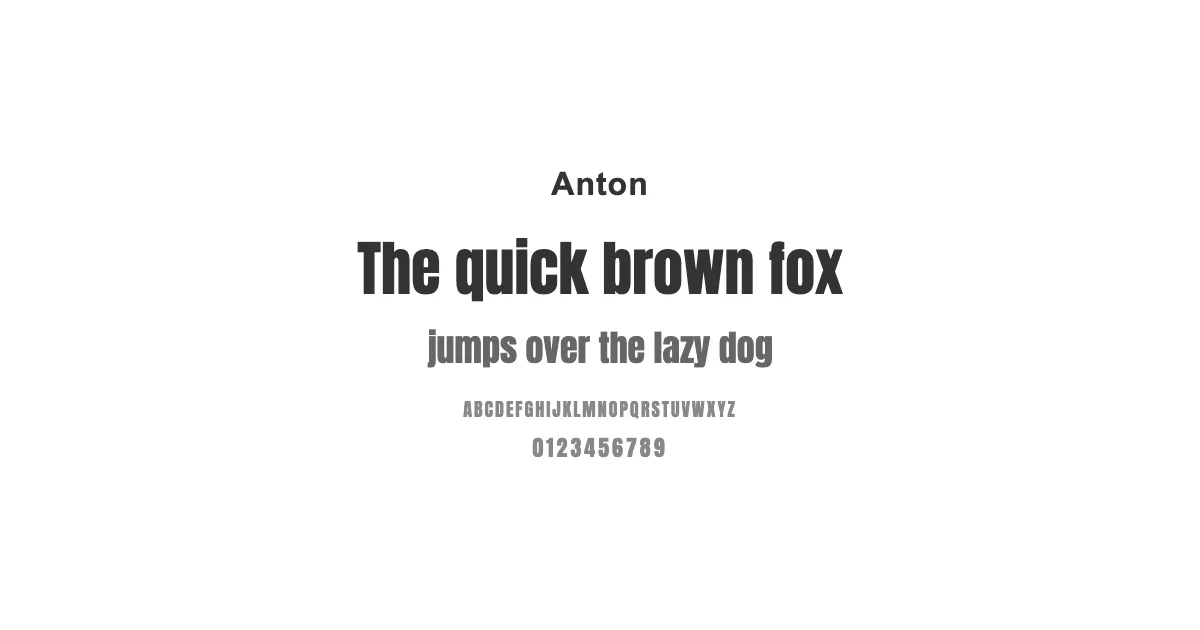
Open Sansは、クセがなく、非常に読みやすいサンセリフフォントです。親しみやすい印象を与えつつ、プロフェッショナルなデザインにも適しています。本文やUIデザインに最適で、幅広い用途で利用できます。
Miltonian/Miltonian Tattooは、レトロな雰囲気の手書きフォントです。個性的なデザインで、他とは違うユニークな印象を与えます。ヴィンテージ感を出したい場合や、特定のテーマに合わせたデザインに最適です。
Latoは、Open SansやHelveticaに似た、クセがなく可読性の高いサンセリフフォントです。数字も美しく、使いやすいのが特徴です。柔らかい雰囲気も持ち合わせており、幅広いデザインに適用できます。
Sorts Mill Goudyは、伝統的で美しいセリフフォントです。Garamondに似た上品さを持ちながら、より柔らかく優しい印象を与えます。信頼感と親しみやすさを両立させたい場合に適しており、企業のウェブサイトや教育関連のコンテンツに最適です。
Robotoは、非常に高い可読性を誇るサンセリフフォントです。洗練されたデザインで、様々な用途に利用できます。特に、技術系やビジネス系のウェブサイトに適しており、本文やインターフェースデザインに最適です。
Antonは、縦長のプロポーションが特徴的なサンセリフフォントです。Impactに似た力強い印象を与え、見出しやタイトルに最適です。モダンでシャープなデザインを求める場合に適しています。
Loraは、エレガントで女性らしいデザインに最適なセリフフォントです。高い可読性を持ちながら、洗練された印象を与えるため、本文や見出しに幅広く利用できます。特に、美容やファッション関連のウェブサイトに適しています。
Alluraは、流れるような美しいラインが特徴的な筆記体フォントです。エレガントで洗練された印象を与え、女性向けのウェブサイトや、ウェディング関連のデザインに最適です。見出しやロゴ、招待状などに利用すると、上品さを演出できます。
Josefin Sansは、幾何学的なフォルムが特徴的なサンセリフフォントです。レトロで可愛らしい印象を与え、個性的でおしゃれなデザインに最適です。見出しやロゴ、短いテキストに利用すると、デザインにアクセントを加えることができます。
Cormorant Garamondは、Garamondの影響を受けた、優雅でクラシカルなセリフフォントです。洗練された美しさを持ち、文学的なコンテンツやアート関連のウェブサイトに最適です。上品で落ち着いた雰囲気を演出したい場合に適しています。